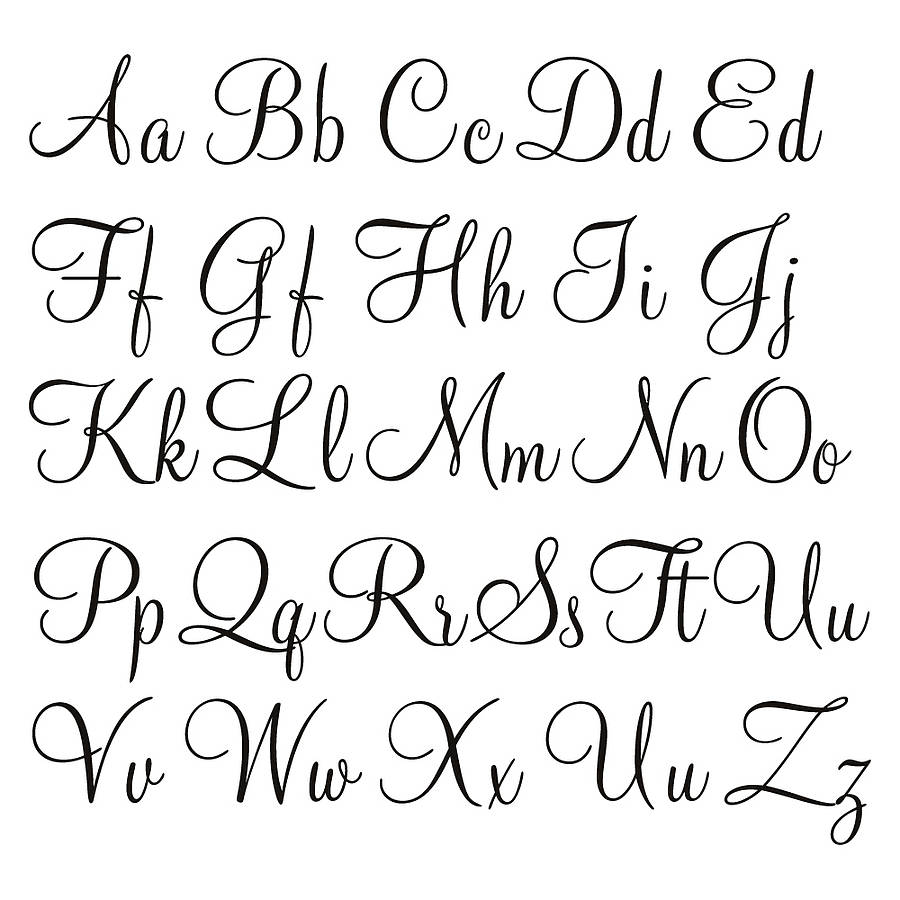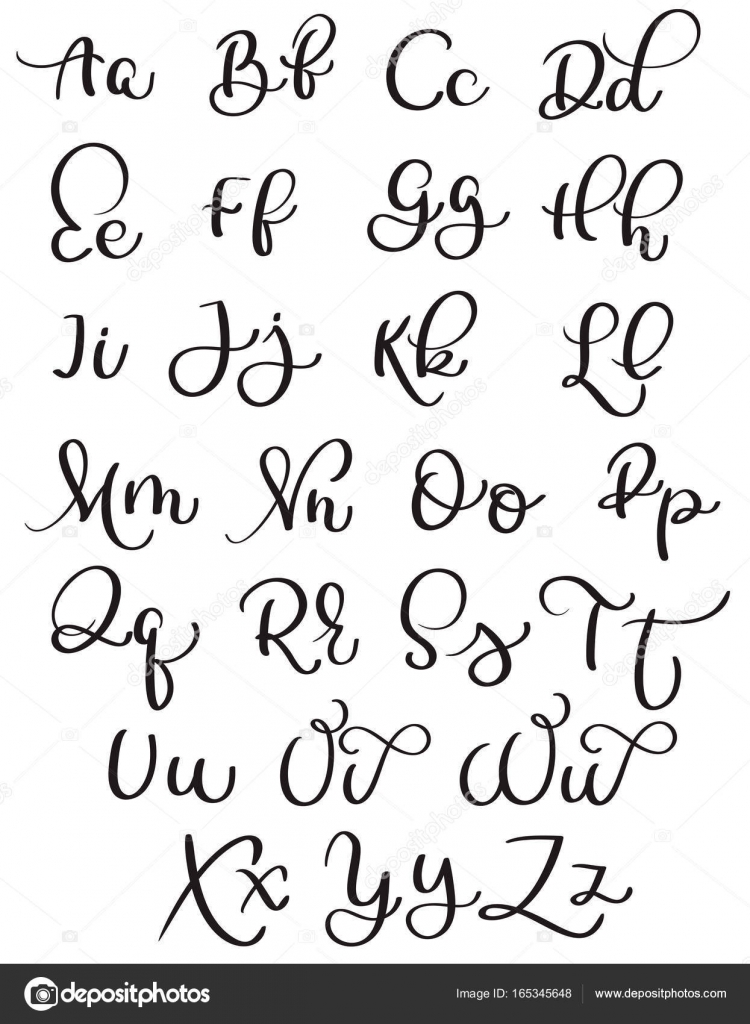
Виды шрифтов в CSS • Vertex Academy
Привет! В этой статье мы продолжим знакомство с CSS, а именно поговорим о шрифтах.
Шрифты — важная часть вида веб-страницы. Существует множество различных, не похожих друг на друга шрифтов.
Тем не менее, все шрифты можно разделить на 4 группы:
- с засечками (serif)
- без засечек (sans-serif)
- рукописные (handwritten)
- моноширинные (monospace)
Давайте посмотрим на следующую картинку:
Слева мы видим шрифт без засечек, справа — с засечками.
Шрифты с засечками по-английски называются «serif» (англ. «serif» — «засечка», «выступ», «штрих»).
- Times New Roman
- Georgia
- Cambria
- Verdena
Шрифты из данной группы обычно используются для длинных текстов, поскольку считается, что их легче воспринимать благодаря засечкам.
Группа 2 — шрифты без засечек (sans-serif)Шрифты без засечек (‘»sans-serif», от фр. «sans» — «без», и англ. «serif» — «засечка»).
К шрифтам без засечек относятся, например:
- Arial
- Helvetica
- Tahoma
Шрифты без засечек часто используются для заголовков.
Стоит также сказать, что шрифты данной группы считаются менее читабельными, чем шрифты с засечками — хотя по этому поводу нет единого мнения.
Вот Вам пример рукописного шрифта:
Рукописные шрифты обычно используются для декоративных элементов на страницах.
Группа 4 — моноширинные шрифтыМоноширинные шрифты — это шрифты, в которых ширина всех букв одинаковая.
Например:
ЭТО МОНОШИРИННЫЙ ТЕКСТ
К моноширным шрифтам относятся, например:
- Courier New
- Lucida Console
Моноширными шрифтами часто пишется программный код.
Например, если Вы пользуетесь текстовым редактором Sublime Text, тогда знайте, что когда Вы набираете код в Sublime, Вы его набираете моноширным шрифтом 🙂
Действительно — зачем? Разве мы как разработчики не должны просто подключить шрифт, который указан в задании?
Все дело в том, что может так получиться, что человек зашел к Вам на сайт, а при разработке сайта использовали такой шрифт, который по тем или иным причинам не установлен у него на компьютере. И все, беда… Чтобы перестраховаться от таких ситуаций необходимо использовать такое понятие как fonts fallback или просто «фоллбэк».
Пример fallback:
p{font-family:»Times New Roman», Georgia, serif;}
p{font-family:»Times New Roman», Georgia, serif;} |
То есть этой строчкой мы указали, что:
- Все параграфы должны отображаться шрифтом Times New Roman.
- Если же вдруг у пользователя нет такого шрифта на компьютере, тогда все тексты параграфов необходимо отображать шрифтом Georgia.
- Если же и этот шрифт не найдется на компьютере пользователя, тогда отображать любым стандартным шрифтом, относящимся к группе шрифтов с засечками (serif).
Как видите, fallback читается браузером слева — направо.
ИТОГО:
Выделяют 4 группы шрифтов:
- с засечками (serif)
- без засечек (sans-serif)
- рукописные (handwritten)
- моноширинные (monospace)
Front-end разработчику необходимо знать какие есть виды шрифтов, например, для написания fallback.
club Очень часто нам приходится сочетать иллюстрацию со шрифтом и многие ломают голову над тем, как сделать так, чтобы шрифт подошел к тому, что нарисовано. Из своего опыта решила написать краткий ликбез.Антиква — Из лат. antiquus – древний.
Собирательное название шрифтов с засечками. Форма знаков антиквы происходит от гуманистического минускула (письма) итальянского Ренессанса XIV–XV вв. (строчные) и капитального шрифта Древнего Рима нач. н.э. (прописные). Первая наборная антиква появилась в Италии и Германии во 2-й половине XV в. и была значительно усовершенствована в 70-х гг. XV в. в Венеции Николаем Йенсоном (Nicholas Jenson). Термин «Антиква» (Antiqua) заимствован из немецкого языка (где он обозначает любой шрифт прямого начертания) и указывает на его древнее (античное) происхождение, поскольку каролингское письмо VIII–IX вв.
Гротеск
Рукописные и каллиграфические шрифты.
Рукописные шрифты делятся в зависимости от пишущего инструмента на шрифты, имитирующие письмо ширококонечным пером, остроконечным пером, кистью и другими инструментами (карандаш, фломастер, шариковая ручка и т.д.). Кроме того, рукописные шрифты могут быть связные (где каждая буква соединяется с соседними) и несвязные (где каждая буква стоит отдельно). Возможны также промежуточные (полусвязные) формы, где соединяется только часть букв или буквы соединяются только с одной стороны. Рукописные шрифты применяются для акциденции и для набора учебной литературы (прописи).
Есть еще всякие декоративные и фэнтезийные, сложные шрифты, не относящиеся ни к одному из вышеперечисленных разделов. Вообще все это деление достаточно условно, я читала массу всяких классификаций, основные это все таки антиквы и гротески.
Латинская каллиграфия
Латинский шрифт был определяющим компонентом западной каллиграфии и был разработан в Риме в различных форматах. Римские имперские столицы, римские прописные буквы и деревенские заглавные буквы используются специально для различных носителей и целей.Развитие продолжалось в течение 2 -го -го и 3 -го веков, когда был создан унциал, который стал очень важным для монастырей, особенно при копировании Библии. Благодаря монастырям они смогли сохранить древнее каллиграфическое наследие в пределах 4 и 5 веков, когда западный мир прошлого подпал под Средневековье. Унциал генерировал самые разные формы в зависимости от того, где он использовался. Стили зависят от монастырей.Некоторые из этих форм имеют скорописный характер, и, как некоторые современные курсивные шрифты, их не очень приятно читать, особенно в расширенных текстах.